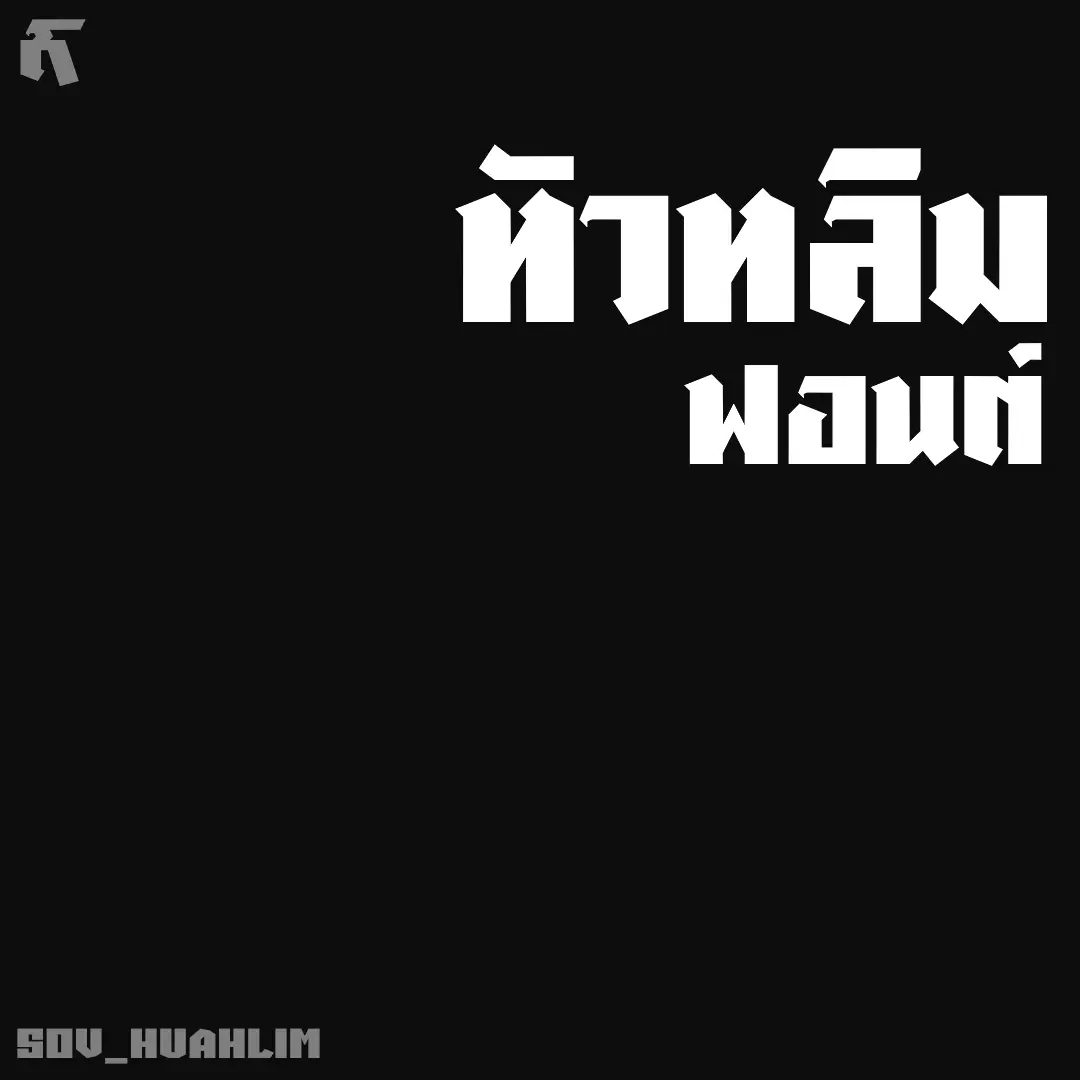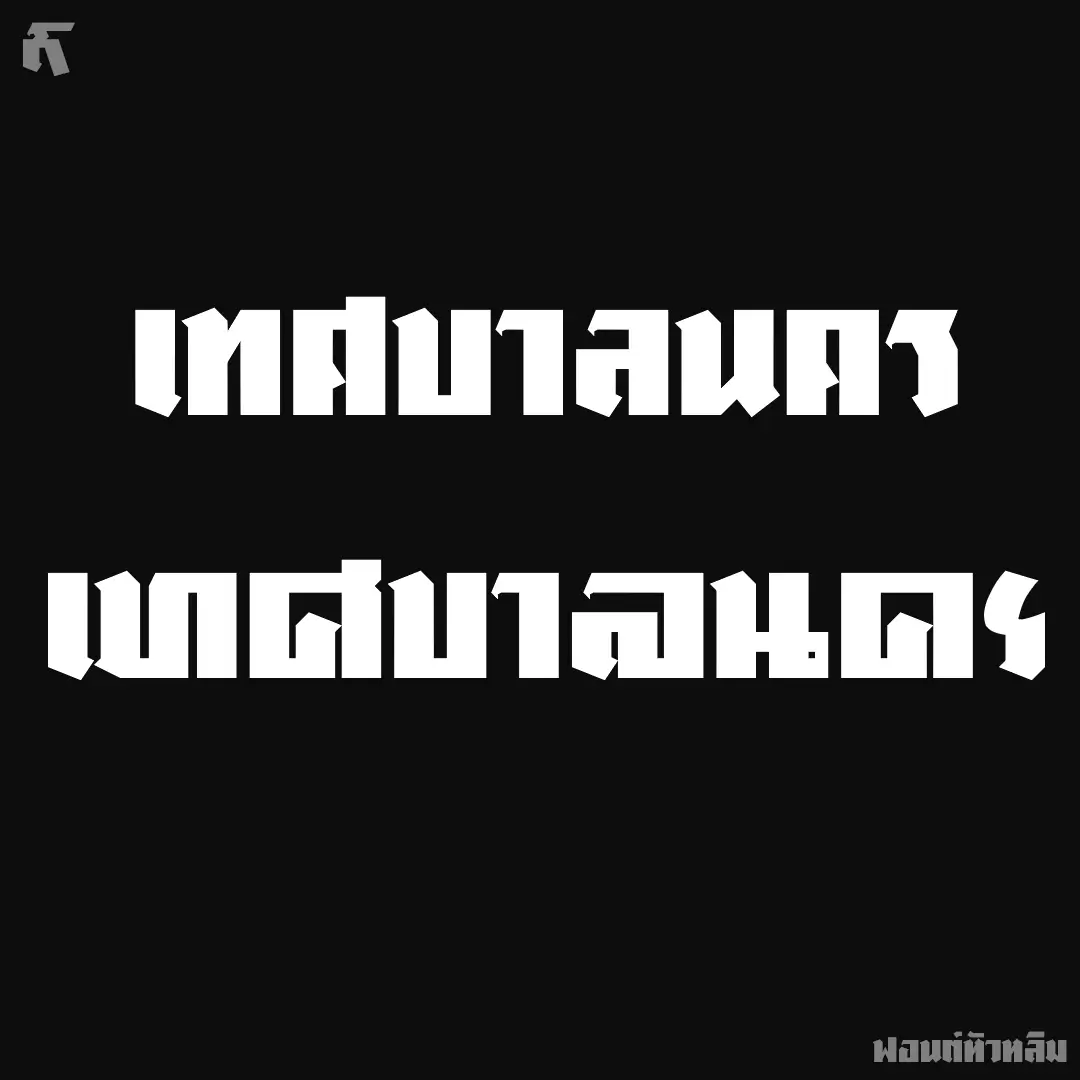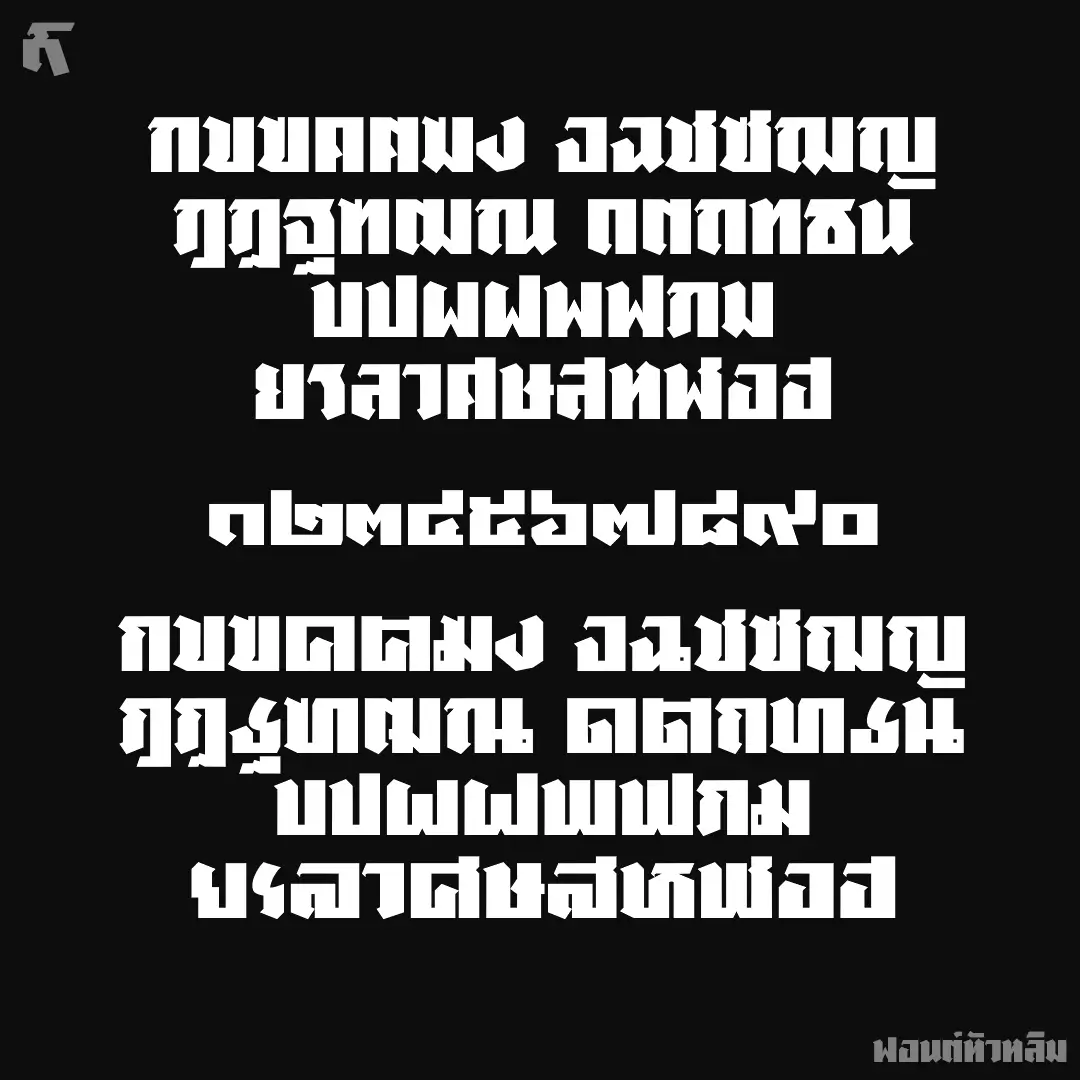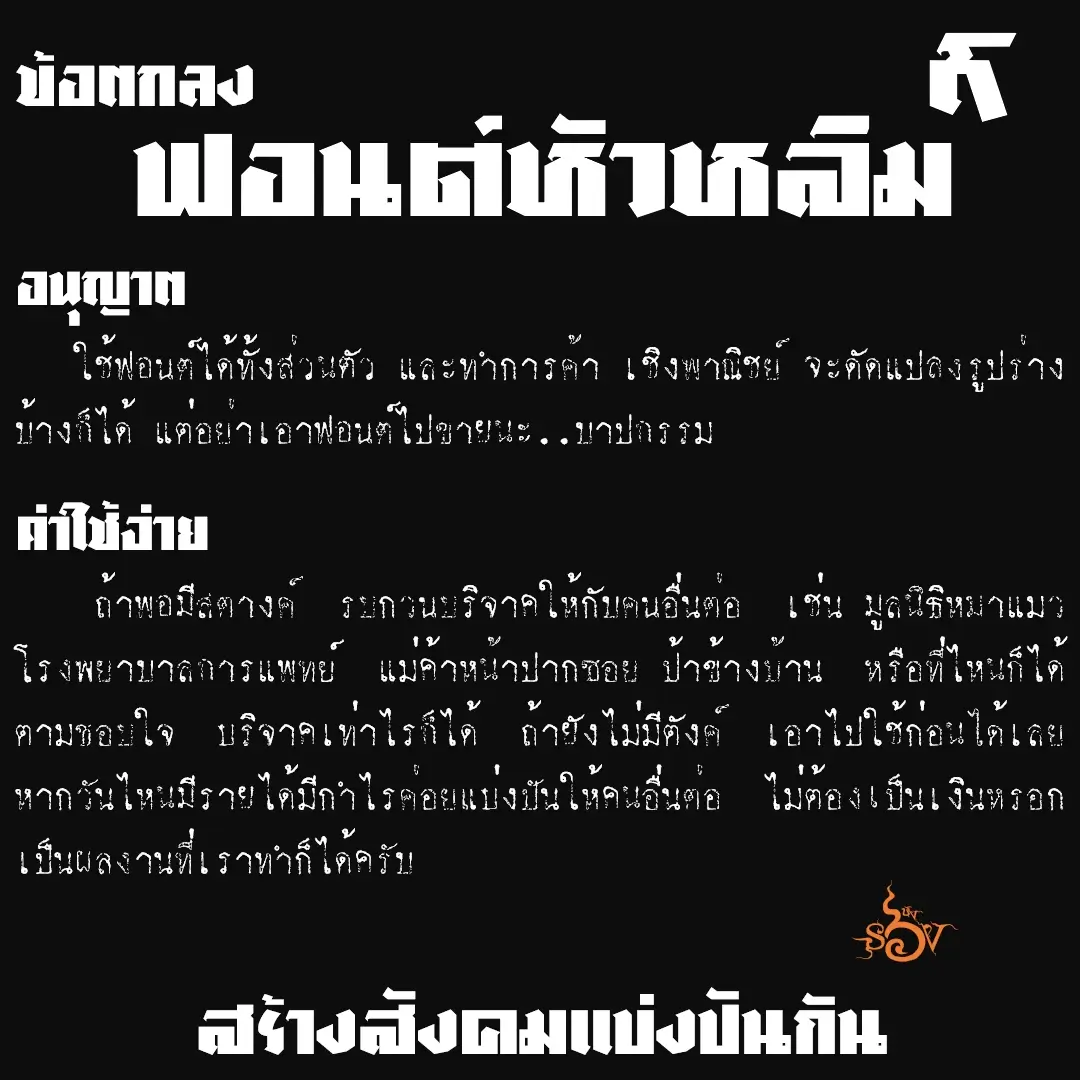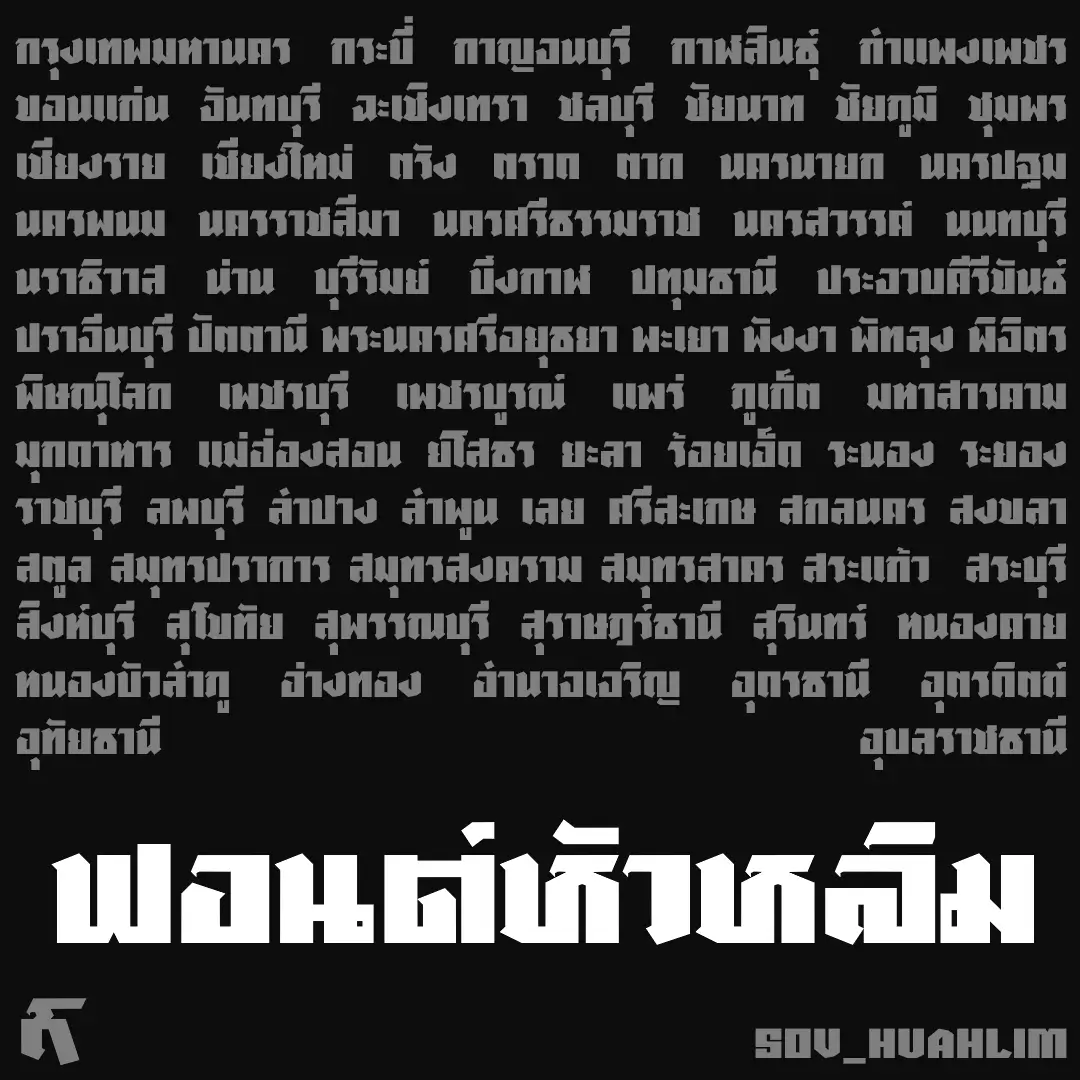
ฟอนต์หัวหลิม – แนวทางจากปกนิตยสาร และป้ายที่พัก ตัวอักษรมีหัวหักมุมเล็กๆ มีมุมแหลมนิดๆ ขออนุญาตเรียกฟอนต์หัวหลิม ส่วนตัวอักษรปรกติสองเส้นตั้ง ตัวหนาสามเส้นตั้ง
เบื้องหลังการออกแบบ : ฟอนต์ หัวหลิม
หัวหลิม (SOV_HuaHlim)